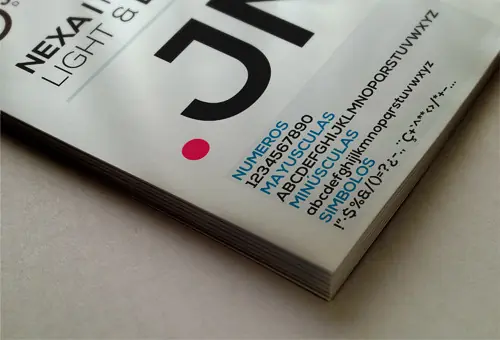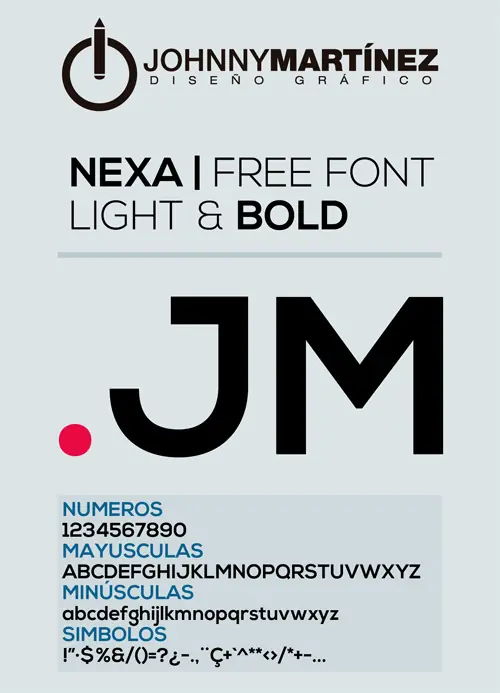
Les presento "Nexa". Una fuente muy bonita excelente para diseño gráfico. Es gratuita y la podemos descargar desde:
Les dejo algunas imágenes para que vean algo del uso que le pueden dar.